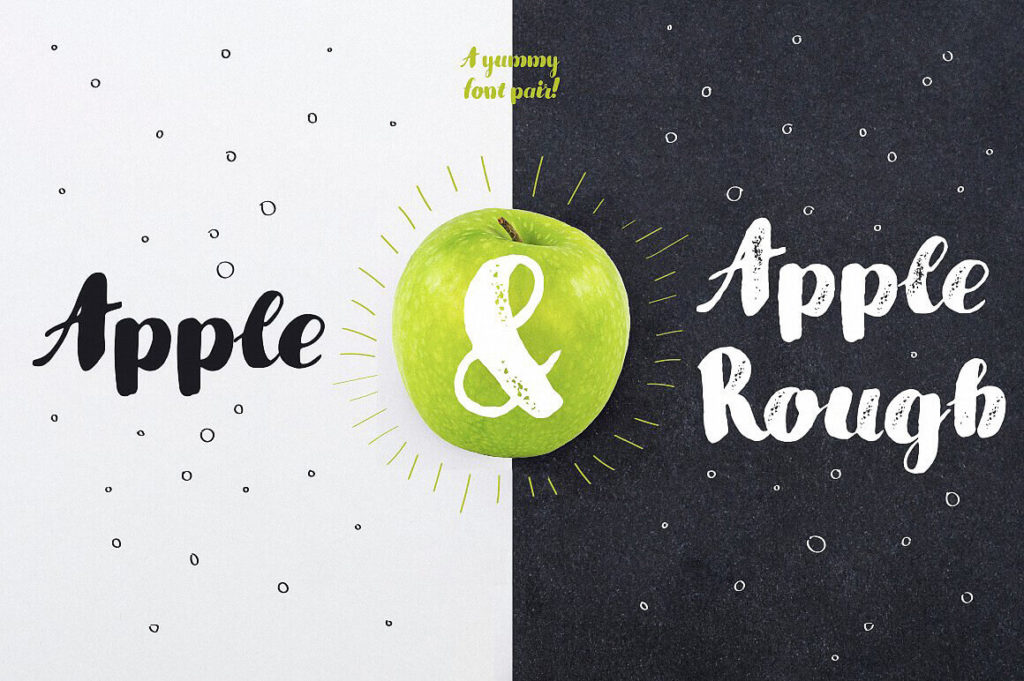
это выразительный акцидентный шрифт с характерной текстурой «grunge» и эффектом потертости. Он создан для создания ярких, брутальных заголовков и привлекает внимание своей небрежной эстетикой. Шрифт полностью поддерживает кириллицу, что делает его отличным выбором для русскоязычных проектов, требующих выразительности и характера. Благодаря грубой фактуре букв, он отлично передает настроение винтажа или индустриального стиля